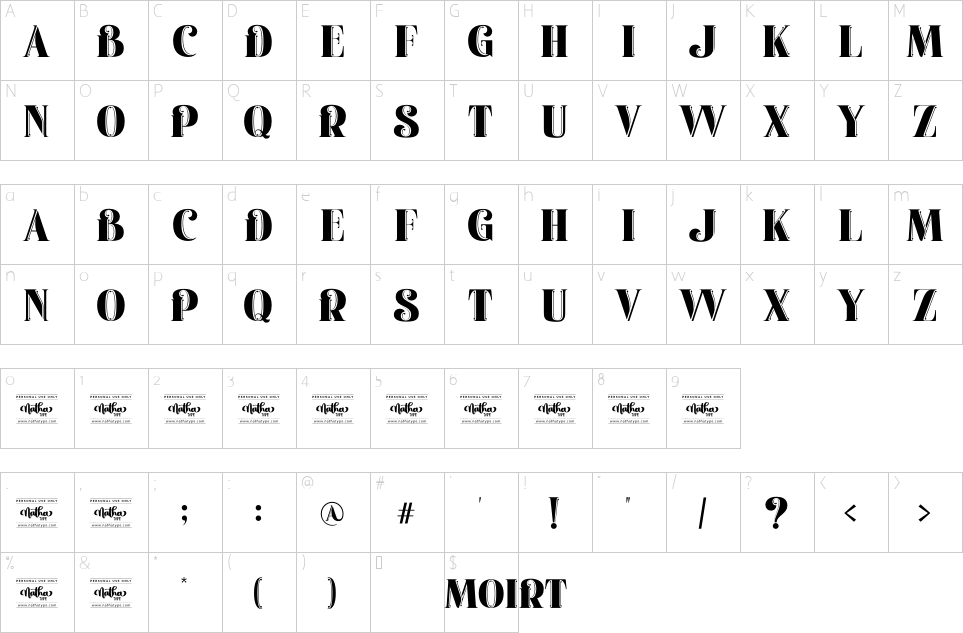
A fonte Moirt é um recurso grátis para designers e estilistas de web de todo o mundo. Cada pixel desta elegante fonte foi cuidadosamente projetada por Natha Type, criando uma experiência de uso fluida e agradável tanto em sistemas Windows quanto em Mac. Com seu design minimalista e sofisticado, Moirt é perfeito para um amplo range de aplicações, desde efeitos visuais complexos até pequenos detalhes em designs de marca. Recentemente, mais de 990 pessoas já deram o pontapé inicial para o seu uso, baixando Moirt gratuitamente para usar em seus projetos. Se você está procurando por uma fonte moderna e atraente que se destaca de outras, Moirt é uma ótima escolha.